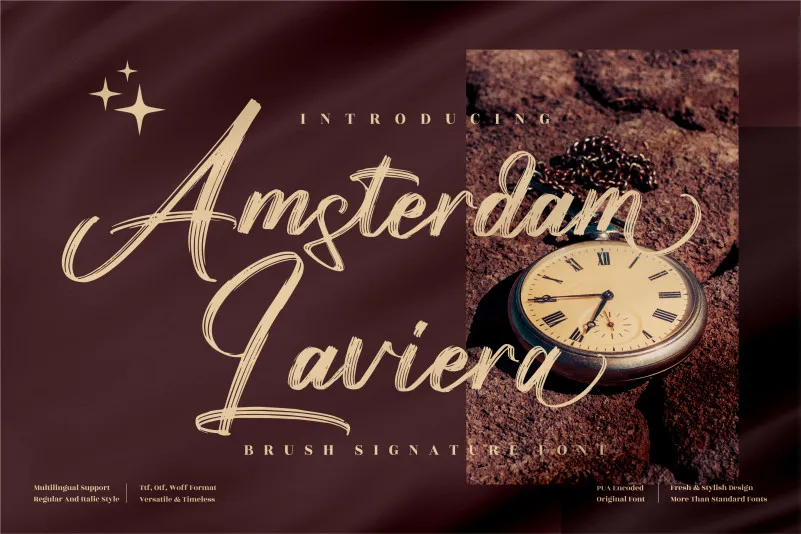
A Amsterdam Laviera Font é uma elegante e versátil escolha para designers que buscam dar um toque autêntico a seus projetos. Seu traçado feito à mão oferece uma graça e fluidez únicas que se combinam perfeitamente com diversas aplicações, como logomarcas, projetos de marca, designs para casa, embalagens de produtos, tigelas, citações, posteres, sacolas de compra, camisetas, capas de livros, cartões de nome, convites e cartas de cumprimentos, etiquetas, fotografia e até mesmo marcas de água. Esta fonte script é ideal para qualquer projeto que exija uma sensação aconchegante e autêntica, garantindo um toque personalizado com estilo. Seja você um designer gráfico ou profissional de marketing, Amsterdam Laviera Font é sua nova parceira perfeita para dar vida aos seus trabalhos em projetos de luxo que exigem uma mão humana delicada.